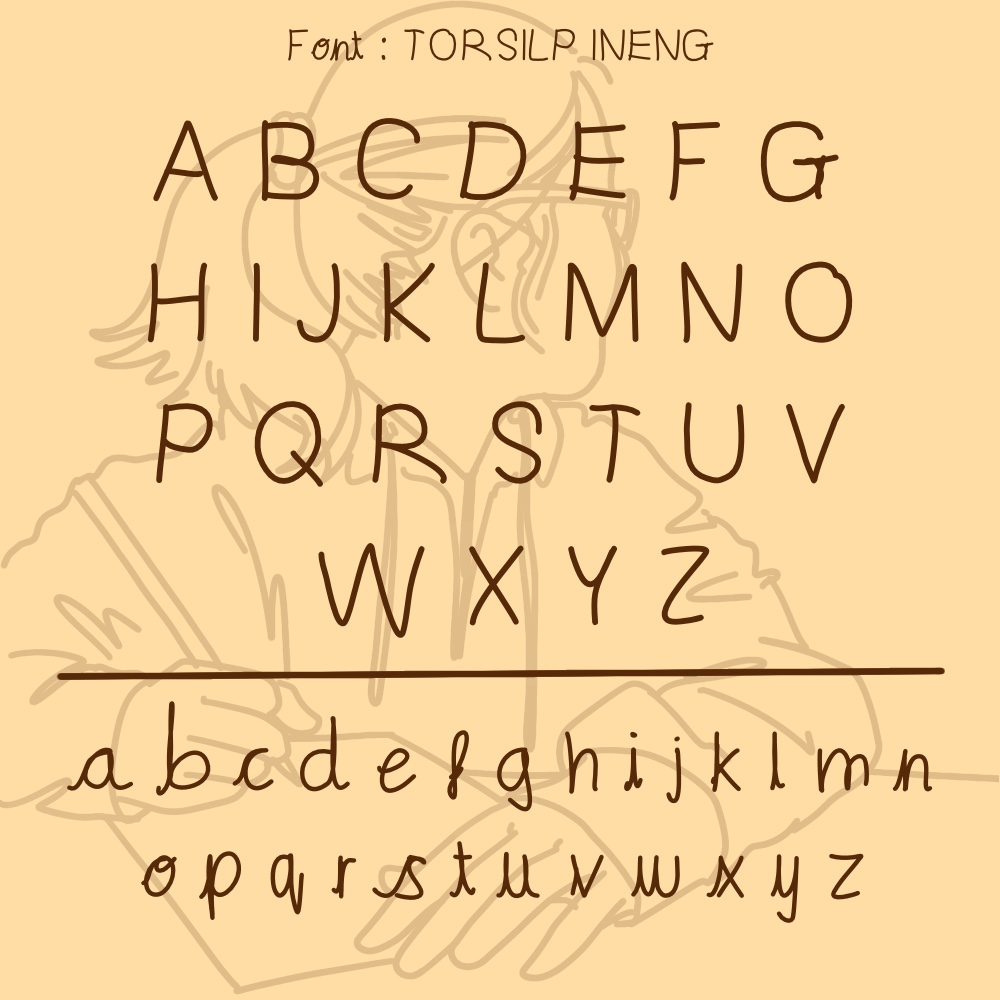
ทอศิลป์อินเอง
ชื่อฟอนต์ : ทอศิลป์อินเอง
เป็นลายมือของลูกศิษย์ชั้นประถม5 ของโรงเรียนสอนศิลปะทอศิลป์
ผมได้นำลายมือของลูกศิษย์มาทำเป็นฟอนต์เพื่อบันทึกเวลาและความทรงจำ
ไว้ในรูปแบบตัวอักษร
ลายมือ "อิงเอง"